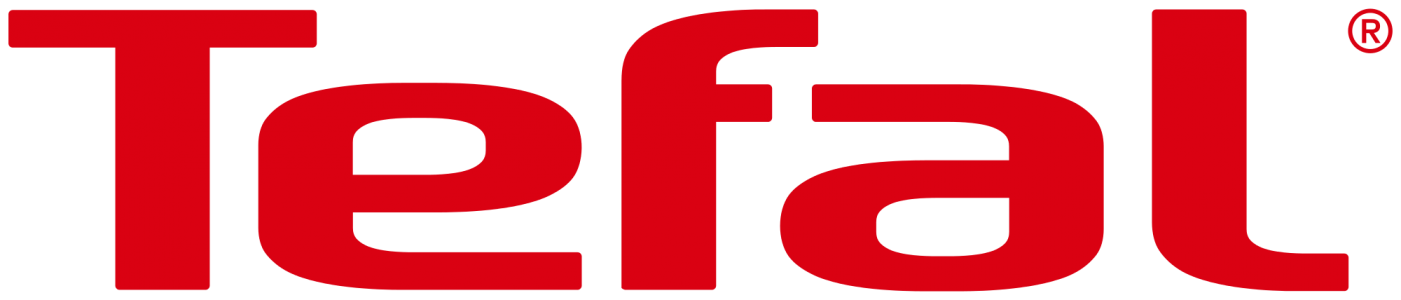
Welche Schrift in "Tefal" Logo?
welche Schrift wird in diesem Logo verwendet?
Das wird einfach ein Logo sein, das nicht aus einer bestehenden Satzschrift aufgebaut wurde.
Letztes Jahr hatten wir hier einen Thread in dem nach einer Schrift mit gleichem a und e gesucht wurde, falls Alternativen helfen würden. Ich finde diesen jetzt nur auf die Schnelle nicht …